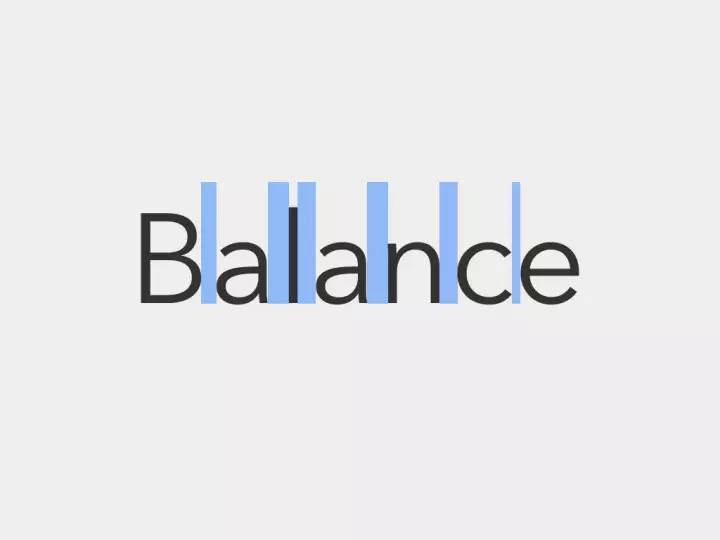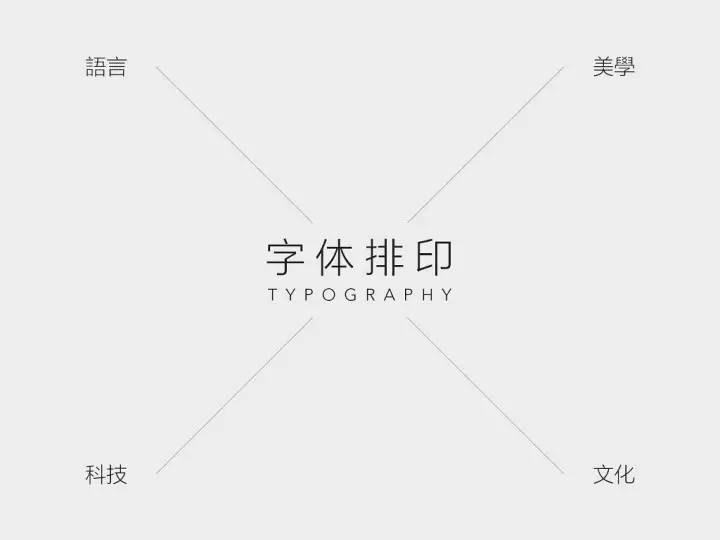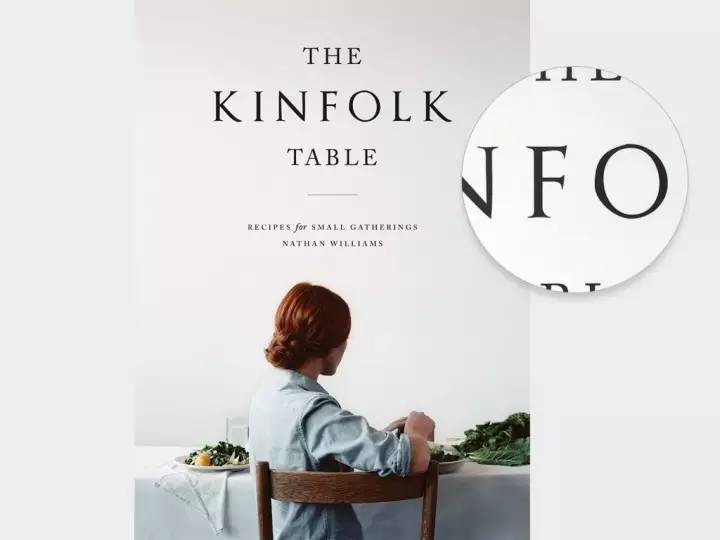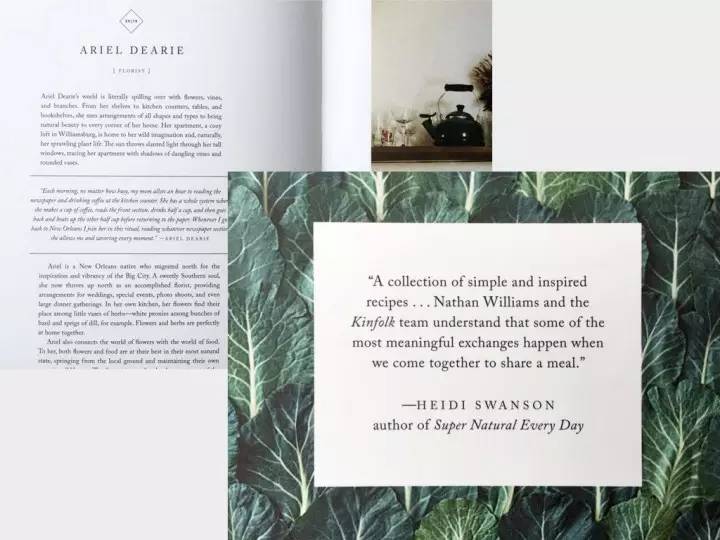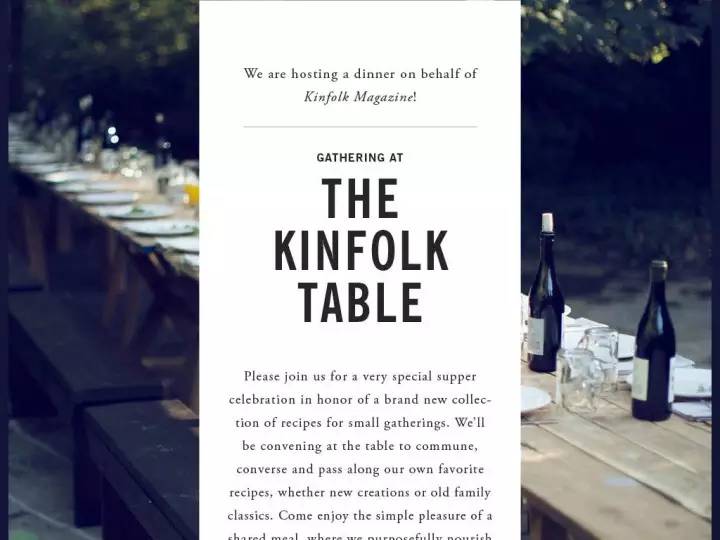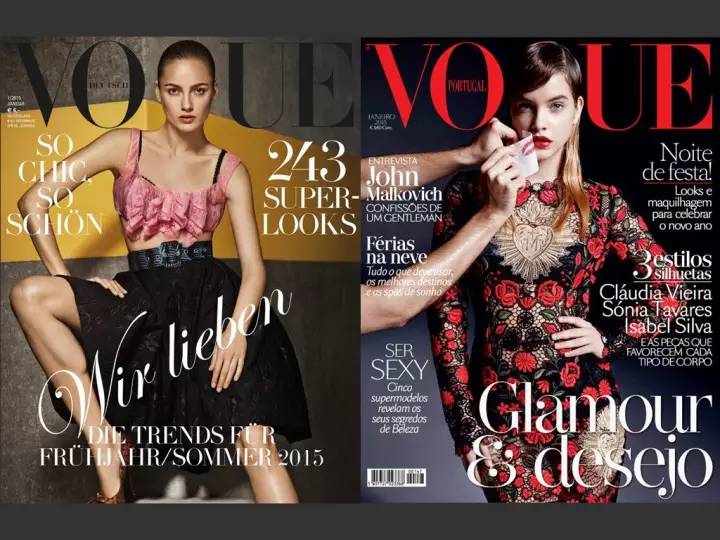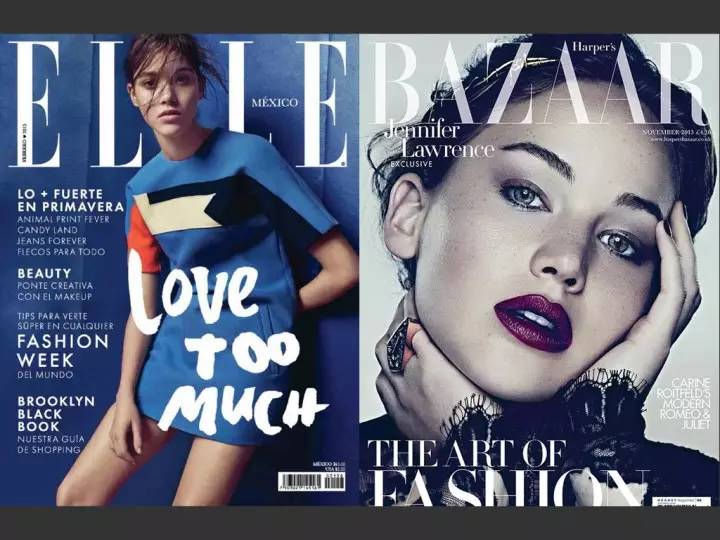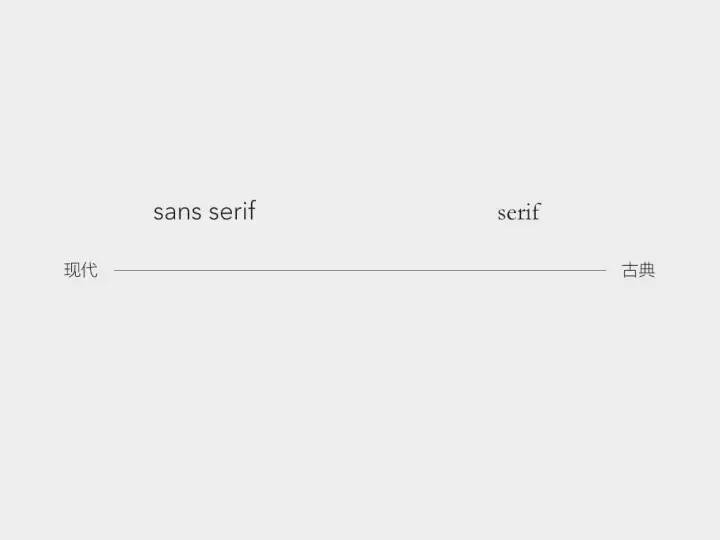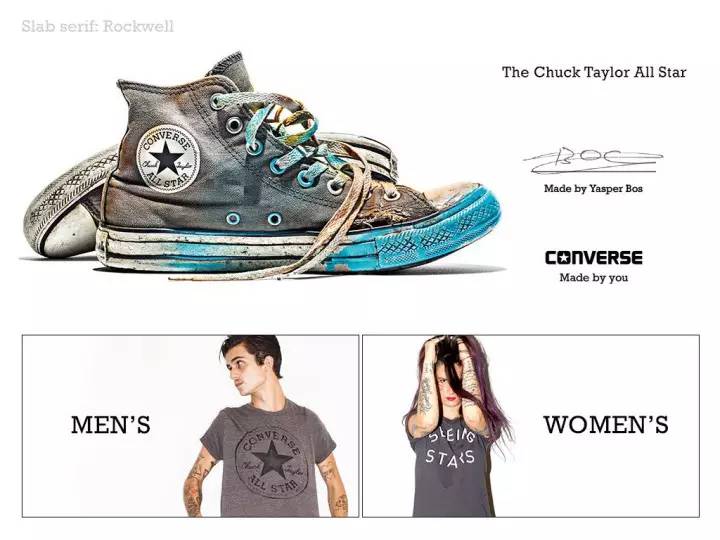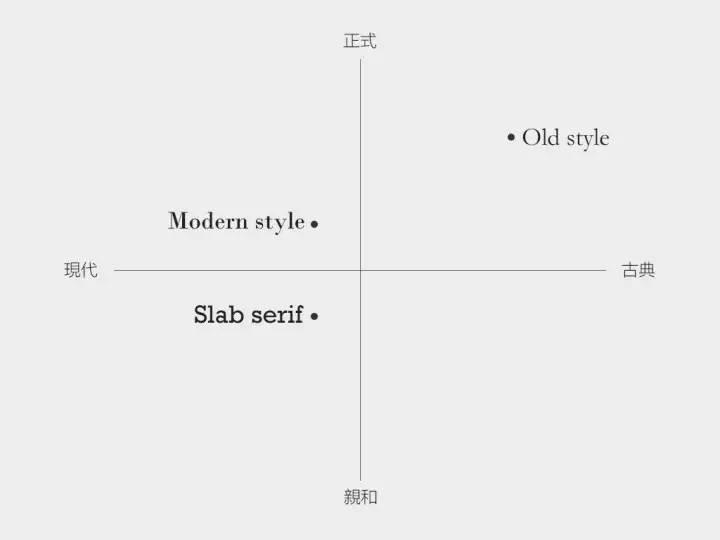
字体设计课程。腾讯设计师自学字体设计课程分享
这是一个给自己准备的字体学习课。
开始的初衷是想解决工作中一些关于字体的疑问(如排版、LOGO设计等),同时也想通过回顾设计的基础知识来提升自己。所以给了自己这个课题,作为初学者只接触到一点皮毛,整理分享出来,如有不足之处烦请指正,所有参考文章标注在文末。
「字体排印」位于语言、文化、科技、美学的交汇处,是一个内涵与外延非常丰富的大话题,这次分享仅选择一些基础的有用知识。
英文字体最简化的分类:衬线体、无衬线体。二者区别在于衬线体有爪形的衬线并且笔划粗细有变化。
一.衬线体
非常古老,可以追溯到古罗马时期的石柱铭文。它风格古典、正式,具有历史传统和意义。
按照历史发展顺序,衬线体可分类为:古罗马体(Old roman),旧风格字体(Old style),过渡字体(Transitional),现代字体(Modern)。我们选取其中两个节点——Old style和Modern字体,通过对比两者特征,就可以理解整个衬线体的发展。
旧风格字体(Old style):
特征:对角强调线,倾斜、括弧型衬线,较缓和的粗细过渡。
风格:传统,常见于书籍、报章杂志的内文排版。
现代字体(Modern):
特征:垂直强调线,水平、极细衬线,强烈的粗细对比。
风格:横平竖直,现代感,高冷。
总结起来,在整个衬线体发展中,笔划对比变得越来越强烈,衬线越来越尖锐纤细,过渡字体的笔划粗细和衬线弧度恰好介于Old style和Modern之间。其一大原因是刻字师傅的技术越来越进步,刻工也变得细腻,使得精确的线条、更精细的粗细对比成为可能。而强调线的倾斜角度也逐渐被「扳直」,这是手工书写向现代排印转变的一个表现。
古罗马(Old roman)、旧风格(Old style)衬线字体案例:
《Kinfolk》是一本推崇慢生活的杂志,常介绍美食、旅行、有格调的家居设计,欣赏微小平淡,返璞归真的美。在此背景下,它的标题使用的是一种古罗马体(Old roman):Optimus Priceps,有一种手工感、古拙的趣味,以及书法的味道。可以注意F衬线左右两边的不对称,以及O笔划的凹凸不平。这种字体风格与kinfolk的定位是相符的。内文使用的有旧风格字体(Old style)Calson和Garamond,相比下我更喜欢下面第三张图内文使用的Garamond,搭配大背景图片和居中排版,显得传统、柔软,有一种诗歌般的美。
现代字体(Modern)案例:
因为现代字体(Modern) 有着锐利的工业感, 同时也保留着传统的衬线元素,显得现代而优雅。所以非常适合时尚工业,Vogue、Elle等杂志都使用了现代字体。许多奢侈大牌也用现代字体作为logo,强调自己百年的传统工艺和优良设计。如使用 Didot的 Giorgio Armani、Burberry,以及使用Bodoni的Valentino。
通常会认为,衬线体代表古典正式,无衬线体代表现代亲和。但衬线体真就不能传达出现代和亲民么?
答案是否定的。Converse所使用的字体Rockwell属于板状衬线体(Slab Serif),如下图所示。它的特点是衬线和字粗细相同,几何与单线设计呈现出现代、年轻的感觉,不似现代体(modern)的精细,适合复古潮牌。
所以字体的情绪其实是相对的,仅在衬线体内部,也有不同情绪的区分。
二. 无衬线体
无衬线体的特征和风格:
(1)完全抛弃装饰衬线,只剩下主干,造型简明有力,更具现代感
(2)适用于标题、广告,瞬间的识别性高
(3)笔画粗细对比小,视觉上看起来基本一致
(4)x高度较高
无衬线体也可以细致的分为四类:早期的无衬线体(Grotesk)、新无衬线体(Neo-Grotesk)、几何无衬线体(Geometric)、人文无衬线体(Humanist)。下文每类选择了一种代表字体来进行介绍,从新无衬线体(Neo-Grotesk)开始。
1. 新无衬线体(Neo-Grotesk):
代表字体是广为人知的Helvetica。用Helvetica作为logo用字体的品牌数不胜数。该字体诞生五十周年时曾有一部纪录片《Helvetica》客观的纪录了它的诞生背景、流行影响、以及各年龄层设计师对它的评价,相信很多设计师已经看过了。
“设计师的生活是战斗的生活,对抗丑陋的战斗。”——《Helvetica》马西莫.维涅里
先谈谈helvetica的优点:
(1)中性
现代主义认为,字体本身只是传达信息的媒介,简明的字体可以让信息更准确地传达,这比视觉表现、风格更重要。因此Helvetica在设计中遵循这一设计理念,保持中性,正如那个比喻说的「字体应该像一个透明的容器」。由于它中性的特征,Helvetica既可以被运用到地铁导视系统,给人有一种现代、高效、清晰的感受,也可以被运用到AA这样的时尚品牌。因为中性,就有了更广阔的运用空间和更开放的解读方式。
(2)具有坚实的形式
在这里说「坚实的形式」而没有说「可读性佳」,是因为它的可读性是有挑战的,但Helvetica确实在字型设计上经过认真考量。在Helvetica之前,广告、杂志上的字体充斥着浮夸花俏的手写体,Helvetica的出现就像一股清流,它去掉了多余设计,关注字体本身的结构,给设计界带来更优质的可选方案。
整体感受是简洁、清晰,没有手工感,非常冷静的字体。细节:
a.切口齐平,笔画始终以水平或垂直收尾
b.顶端平坦
c.方形点
d.据说Helvetica字母包围的面积和它的笔画所占的面积是一样的
e.a的负空间呈水滴型
(3)与瑞士平面设计紧密相关
Helvetica的成功不是它一个字体能够完成的,是跟一系列的新无衬线体(Neo-Grotesk)的出现,以及与整个瑞士平面设计的融合,风靡全球分不开的。它们共同形成了一整套完整的理念:崇尚绝对的理性、客观、系统化。如我们所熟知的网格系统,就是推崇系统性、数学化的视觉体现。
瑞士平面设计的典型手法是以纯粹的文字编排来做极简传达。它在1960年后风行世界,是因为表现简洁、直接,并且在操作上容易标准化、系统化。当时的美国企业正在为全球化扩张寻求一种快速传播并且统一识别性的视觉解决方案,瑞士平面设计、Helvetica的出现加上各种大师的成功运用,把它们一起推向顶峰。
然而Helvetica并不是完美的,在这里归纳三个缺点:
(1)缺乏韵律。Helvetica的设计理念是一致、去个性,字母的整体造型都偏圆,因此缺乏阅读韵律,并且没有针对小字阅读优化,在优秀字体及细分领域都丰富的今天,Helvetica的优势减弱。
(2)中性也是一把双刃剑。冷静,客观的同时,也抹杀情感,忽略了形式可能为用户带来的愉悦。
(3)滥用。可参考今天Flat design的泛滥,误用、滥用造成人们的审美疲劳。
如果你喜欢中性感的字体,又想修正Helvetica的可读性缺陷,可以尝试Univers,比Helvetica更加洗练的造型,并且字重齐全。
另两款新无衬线体(Neo-Grotesk),分别是Helvetica的前身和号称Helvetica killer的字体。
2. 几何无衬线体(Geometric):
代表字体是的Futura。所谓“几何”就是将字母归纳为圆、方、三角等几何形状的字体。
Futura受到包豪斯的影响,造型有设计感。笔划以垂直、水平的硬朗笔划为主。细节:
(1)顶角和底角非常锐利
(2)字母正圆处理
(3)升部降部偏长,优雅
iPhone的报刊杂志icon,「ART」三个字母使用的就是Futura。
Futura在德语拉丁语中是「未来」的意思,因此它除了常见于有设计感的产品,如LV、Omega,也常用于「未来」题材。
在前面的图中可以看到Futura为了保持设计感,j、t省略了尾部,a、g使用单层结构,因此在可读性上有些问题,并不适于内文排版。并且它个性鲜明,有点「抢眼」。如果你喜欢几何无衬线的造型,但又想选择更温和、可读性强的字体,可以尝试Avenir。Avenir虽然同属几何无衬线体,但它在被设计时并不拘泥于几何形式,而是以视觉为准,显得人文、柔和,如a的尾部增加了一点点外翘的小细节。
3. 人文无衬线体(Humanist):
代表字体是Myriad。人文无衬线体具有更好的韵律感,气质开放、亲和,与Helvetica的相比更儒雅,不匠气。下图通过对比可以直观感受到什么是「人文」特征。
(1)人文无衬线体的x-height相对较小,使整体更有韵律。
(2)人文无衬线体的e、s等字母收尾采用半包围结构,更开放,不如Helvetica全包围的那么拘谨,显得亲和随意。
(3)人文无衬线体线条柔美,不是Helvetica的工程感,更流线型,具有一定的手写味
案例:苹果的VI字体,用于宣传:广告、网站、产品铭文等。港铁地图的部分字体。
同属于人文无衬线体的字体还有:Frutiger、Segeo
通常会认为,衬线体代表古典正式,无衬线体代表现代亲和。那么无衬线体就不能表现优雅和古典吗?
答案是否定的。无衬线字体Optima融入了衬线基因,虽然没有衬线,但粗细变化相对明显,比划末端加粗,显得非常优雅有韵味。(在处理logo时如想要既优雅古典,又不显得老陈迂腐,可参考这种思路。)
无衬线字体的情绪轴。
1.视觉平衡
(1)同样粗细的线条,由于视觉误差,水平的看起来要比垂直的更粗。因此在设计英文字母时,就应当充分考虑到视差。小林章的书籍内讲解了很多这样的案例。
(2)Futura是几何无衬线体,它的O看起来像是正圆,当我们和真正的正圆对比时,就会发现Futura的几何形状也是经过优化的,水平方向笔划微调修细。三个「圆」相比,Avenir虽然最不似正圆,但作为字母O却是看起来空间最舒服、最稳定的。
(3)这是是用圆弧和直线拼接起来的O,然而由于视差,却看起来有两侧内陷的错觉。因此在处理时,会讲两侧稍微向外隆起一点点,并微调水平方向的线条,就能把生硬不圆润的圆形变为视觉柔和的O字母了。
(4)X的造型原来不是斜线直接相交的结果,而是把斜线稍微错开,才能看起来像是相连的状态。并且为了避免四条斜线相交造成中间黑色部分太密集,中心位置的笔划略调细了一些。
(5)虽然无衬线体的比划粗细基本一致,但实际还是有着细微的差距。从正面看到的A(左侧图)非常正常,然而当A被水平翻转后(右侧图),立刻就有了略怪异和不稳的感受。A的右侧比左侧笔划粗,是受到历史上平笔书写以及衬线体延续下来的习惯的影响。翻墙看视频《罗马体大写字母使怎么形成的?》
(6)绘制图标时我们都有经验,由于图标外形轮廓和内部复杂程度的不同,视觉体量感是不同的,不能完全依照尺寸大小而要根据视觉感受来判断。字体设计有共通之处。同样字号的文字,圆形O和三角形的A要高于参考线。在做LOGO时可以留心这点,参考案例NIVEA。
2.负空间
负空间指的是字母内部的空间,以及字母与字母之间的空间。在字体设计过程中,设计师不仅要设计字母的笔划结构,更重要的要考虑负空间的设计,使之平衡和协调。引用字体大师马西莫的一句话:「我们通常认为,字体排印就是黑色与白色。而排印实际上是白的,而不是黑的。因为字体是由形体之间的空间来定义的。这有点像音乐,音乐不是由音符,而是由音符之间的停顿来定义的」。据说英文字体设计师对负空间关系的斟酌时间可能占整体字体设计内容的1/3左右。